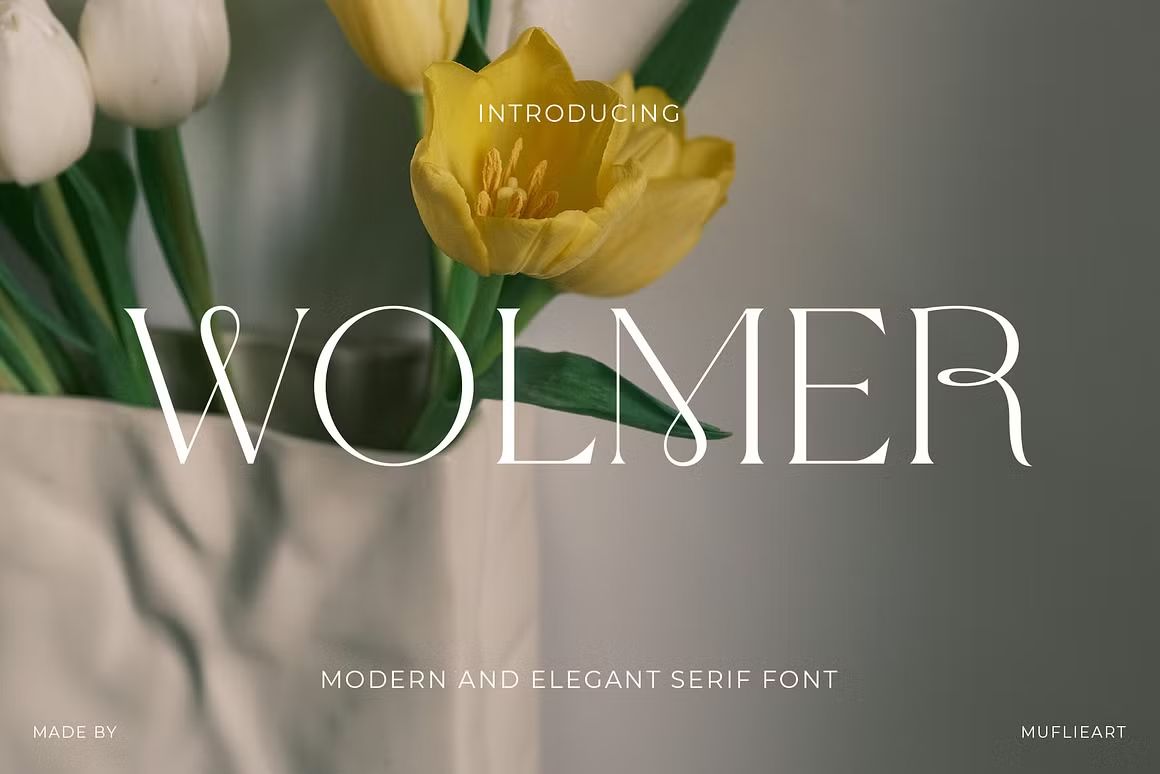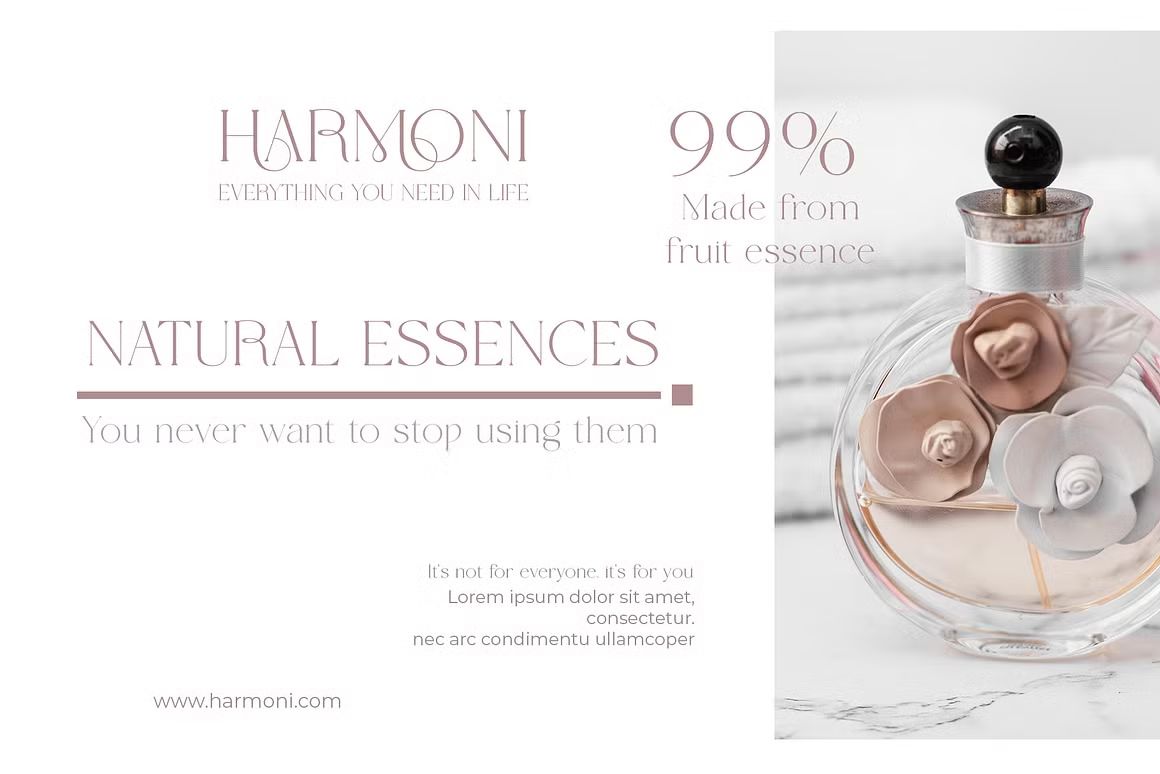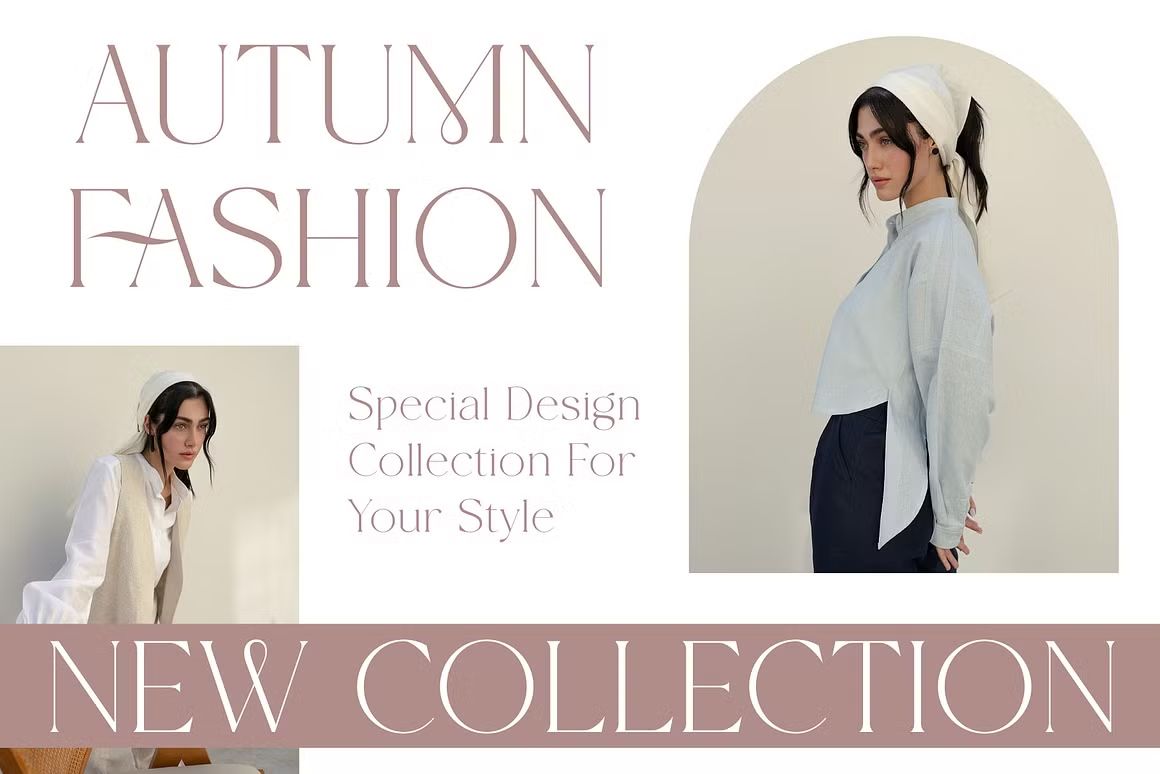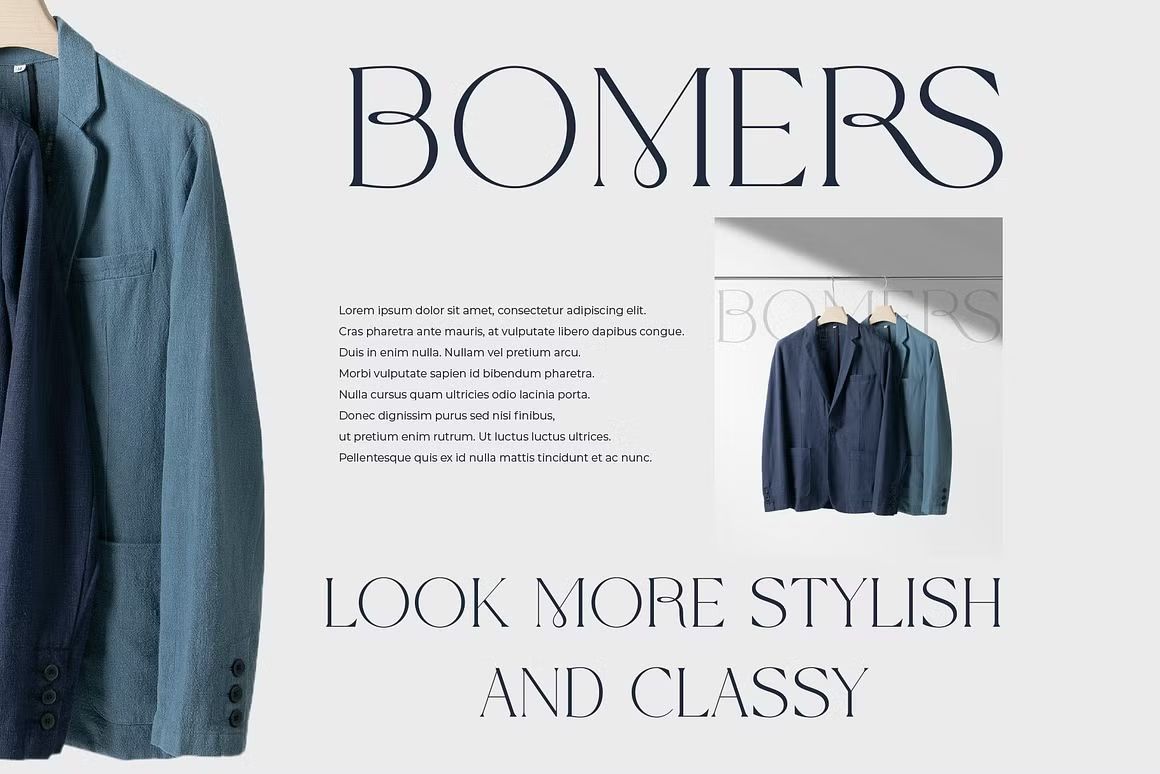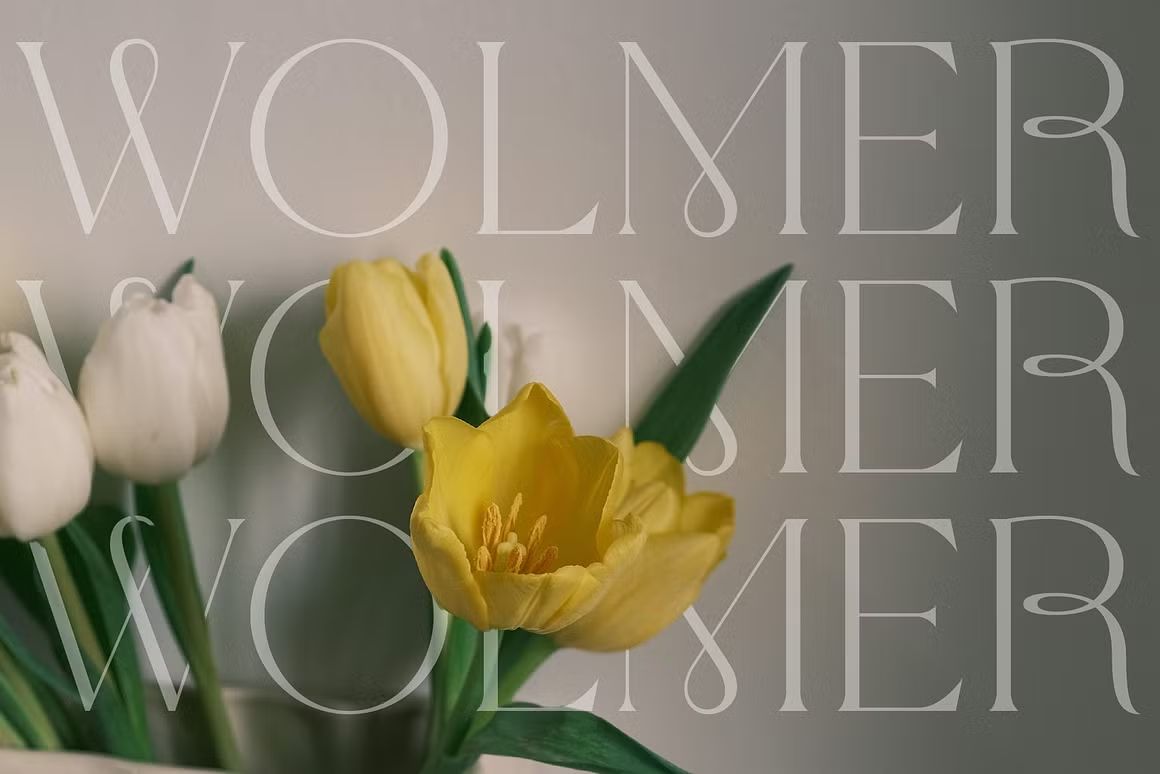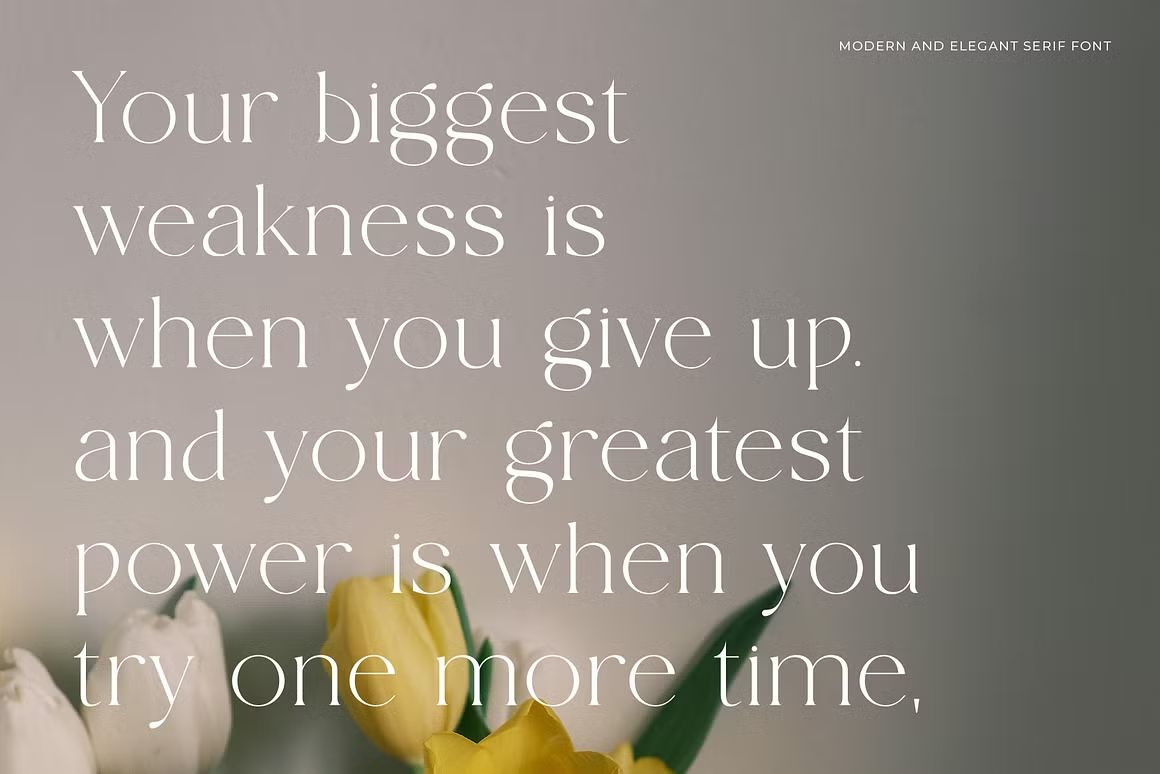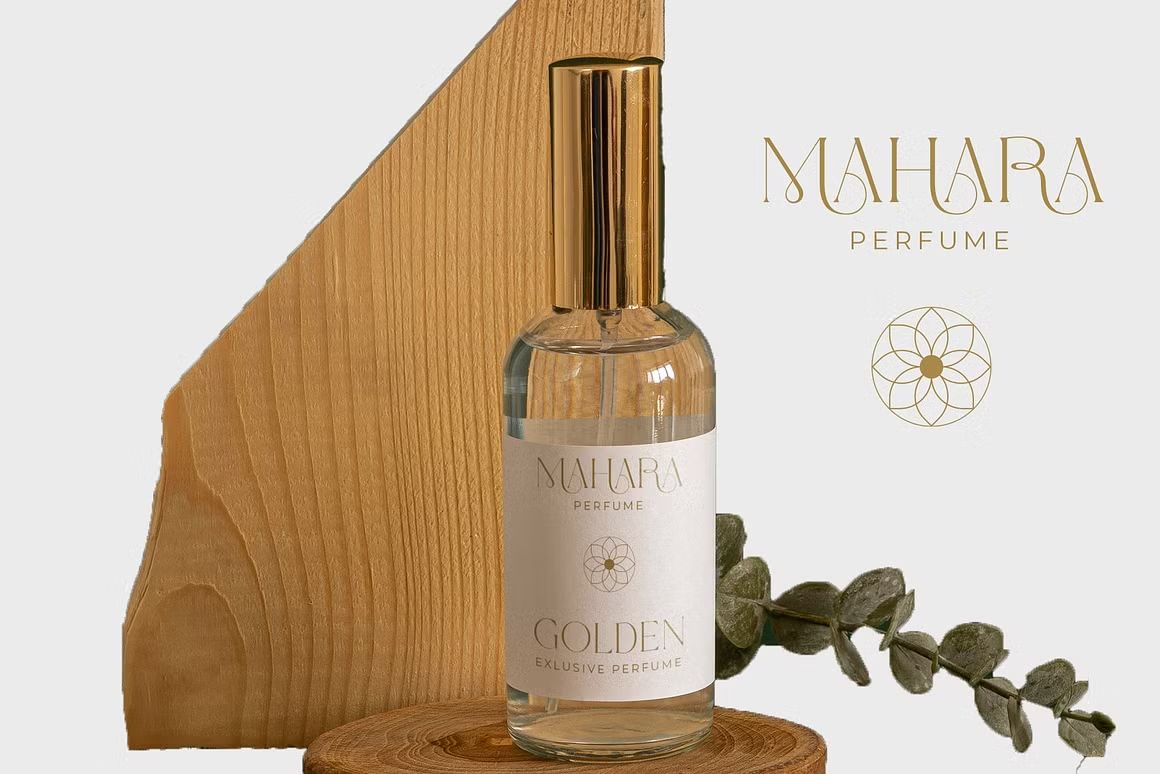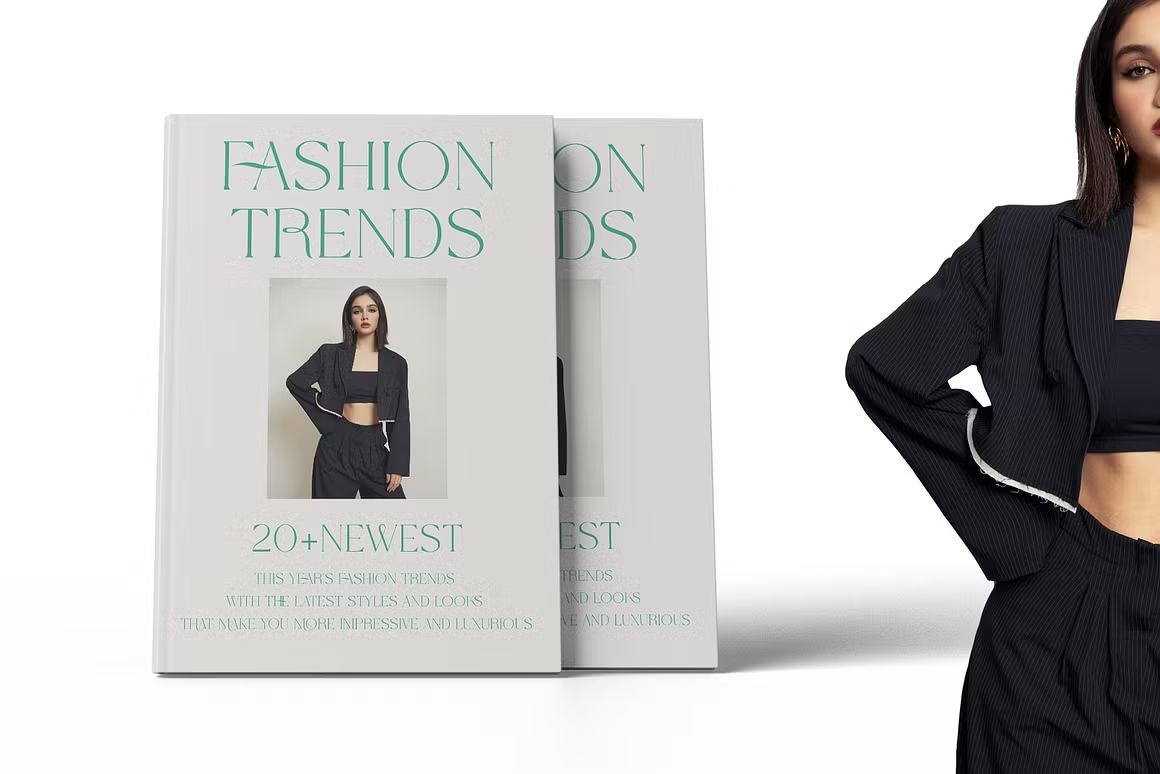
Wolmer – Modern And Elegant Serif
Wolmer adalah font serif modern dan elegan dengan garis tegas dan detail halus, cocok untuk desain editorial, branding, logo, dan proyek kreatif yang mengutamakan kesan mewah dan profesional.
Wolmer adalah font serif modern dan elegan yang dirancang dengan keseimbangan sempurna antara ketegasan dan keanggunan. Dengan bentuk huruf yang bersih dan detail halus, Wolmer memberikan kesan profesional, mewah, dan berkelas, menjadikannya pilihan ideal untuk editorial, branding, logo, kemasan produk, dan berbagai proyek desain premium.
Fitur unggulan:
• Gaya serif modern yang elegan dan profesional
• Cocok untuk branding, editorial, logo, dan kemasan mewah
• Termasuk huruf besar, huruf kecil, angka, dan simbol
• Ideal untuk desain cetak maupun digital yang mengedepankan estetika dan eksklusivitas